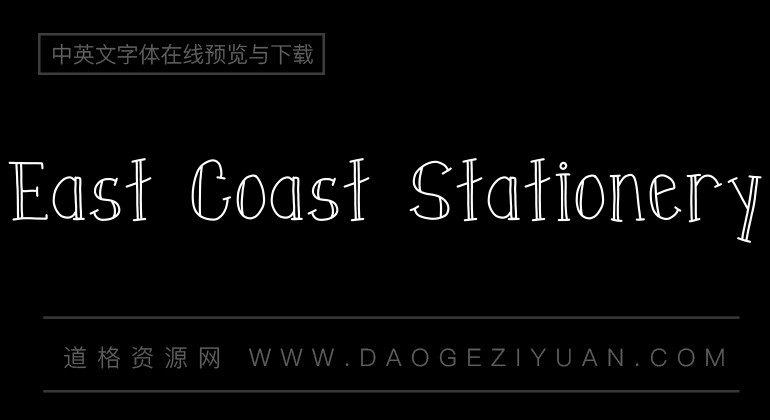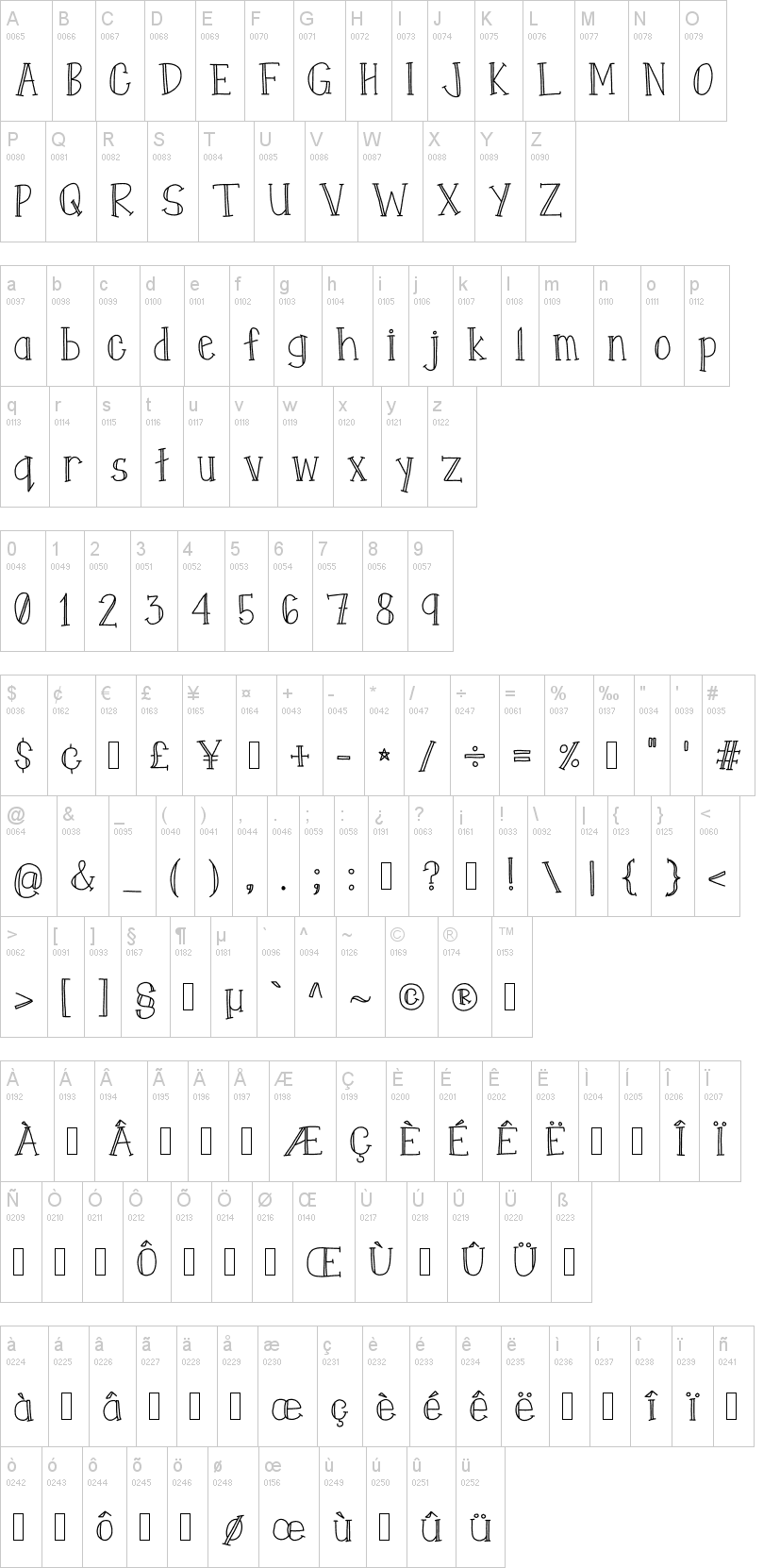
East Coast Stationery
East Coast Stationery字体是一种拥有海滨风格的手写字体,它具有清新脱俗的特点,适合印刷在海滨风格的海报、明信片、名片等上,也可以用于网页设计中。字体的字体结构清晰,字的边缘有柔和的曲线,使得字体看起来更加灵动,显得更加活泼。它拥有良好的可读性,可以满足各种印刷需求,具有良好的可扩展性,可以满足不同尺寸的印刷要求。
East Coast Stationery是一款非常不错的手写艺术字体,具有很好的视觉感,适合于文化类的宣传设计、商业类品牌的广告和产品包装设计以及个性化文字排版等较多场景。